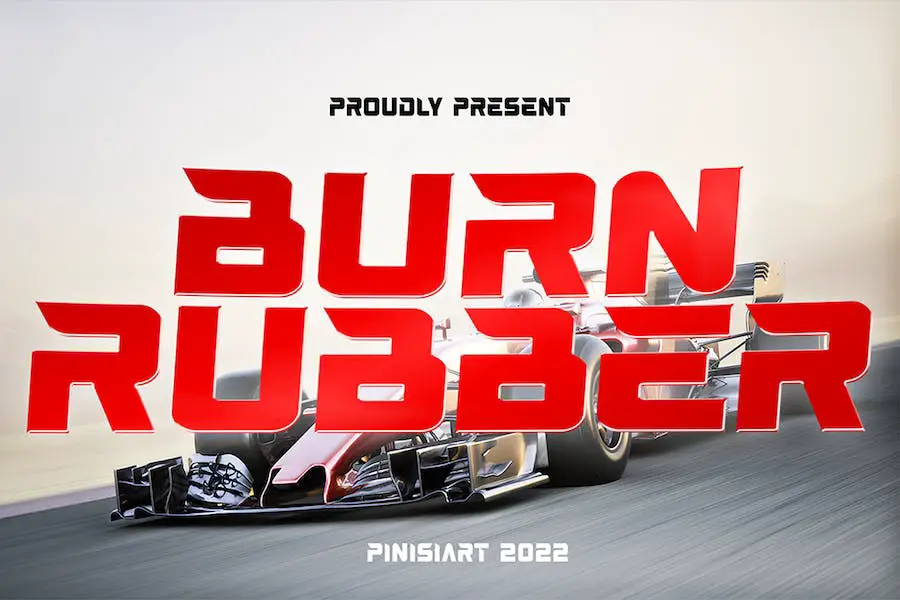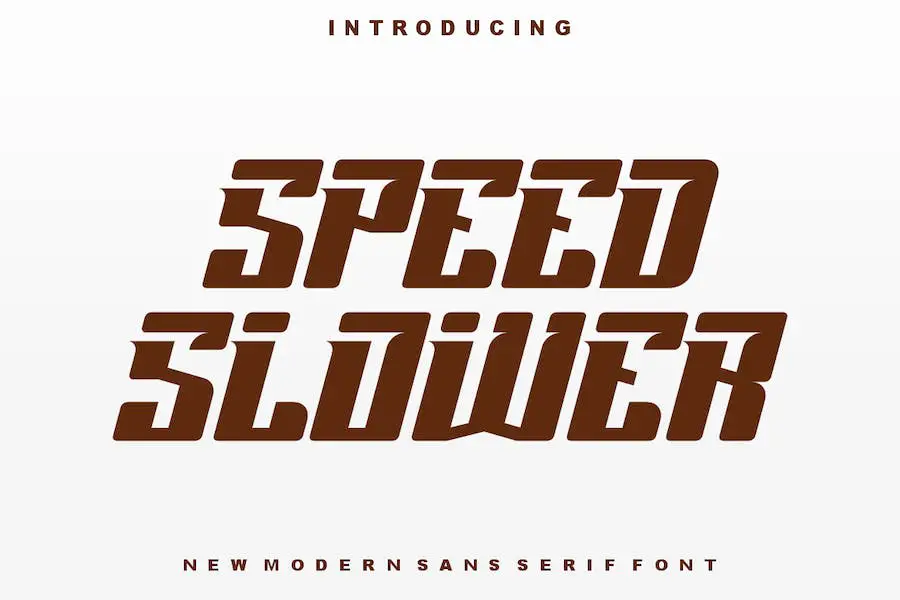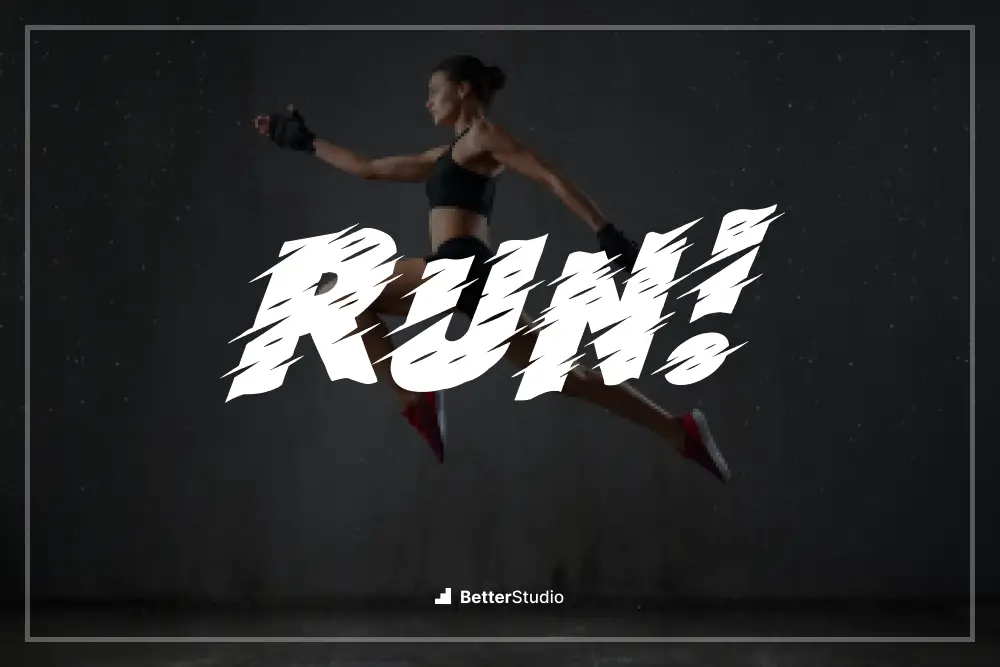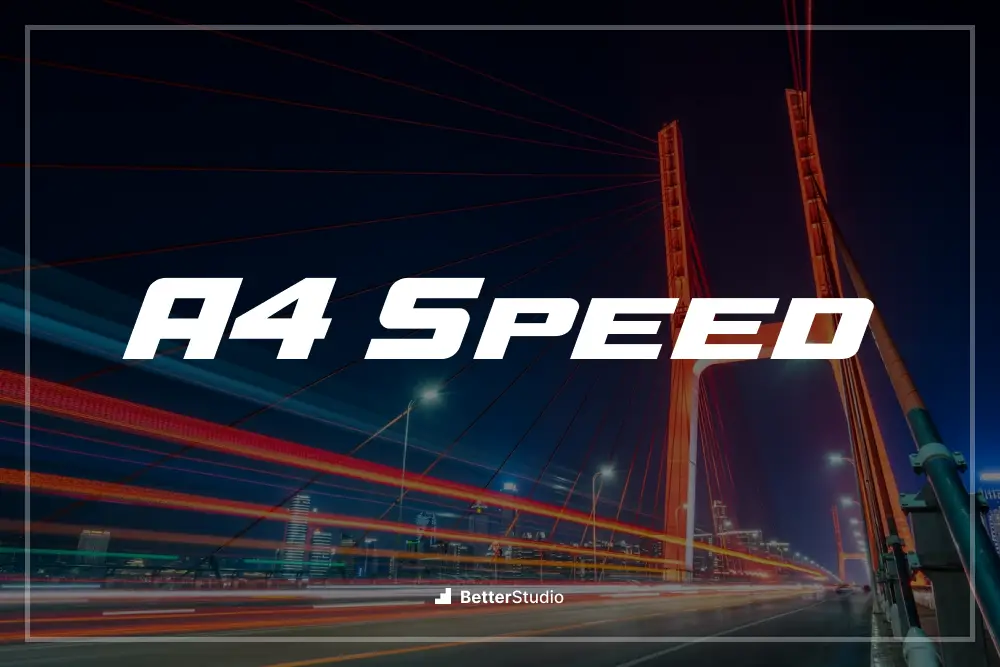
2023 年のベスト Speed フォント 20 (無料およびプレミアム)
公開: 2023-07-31グラフィック デザイン プロジェクトに洗練されたプロフェッショナルな外観を与える完璧なフォントを見つけるのに苦労したことがありますか?
もう探す必要はありません。このブログ投稿では、デザインを次のレベルに引き上げる、無料とプレミアムの両方の 2023 年の最高速度フォント 20 個について説明します。 しかし、なぜスピード フォントに注目するのか疑問に思われるかもしれません。
答えは簡単です。スピード フォントは、可読性と可読性を高めるために特別にデザインされており、視聴者がデザイン内に表示される情報をすぐに吸収できるようになります。
最近の研究によると、インターネット ユーザーの平均注意力持続時間はここ数年で大幅に減少しており、ユーザーの注意を素早く集めることが重要になっています。
実際、調査によると、聴衆に永続的な印象を与えるのに必要な時間はわずか約 8 秒です。
ここでスピードフォントが役に立ちます。 これらのフォントは、すっきりした線、コンパクトな形状、最適化された間隔により、メッセージを迅速かつ簡単に配信します。
この記事では、デザイン プロジェクトを確実に向上させる、厳選された 20 倍速のフォントを紹介します。
ポスター、Web サイト、ロゴ、その他のビジュアル素材のいずれを扱う場合でも、これらのフォントは、視覚的に魅力的で理解しやすいコンテンツを作成するのに役立ちます。
それでは、早速、スピード フォントの世界に飛び込み、次のプロジェクトに最適なタイポグラフィを見つけてみましょう。
最高のプレミアムスピードフォント
高速
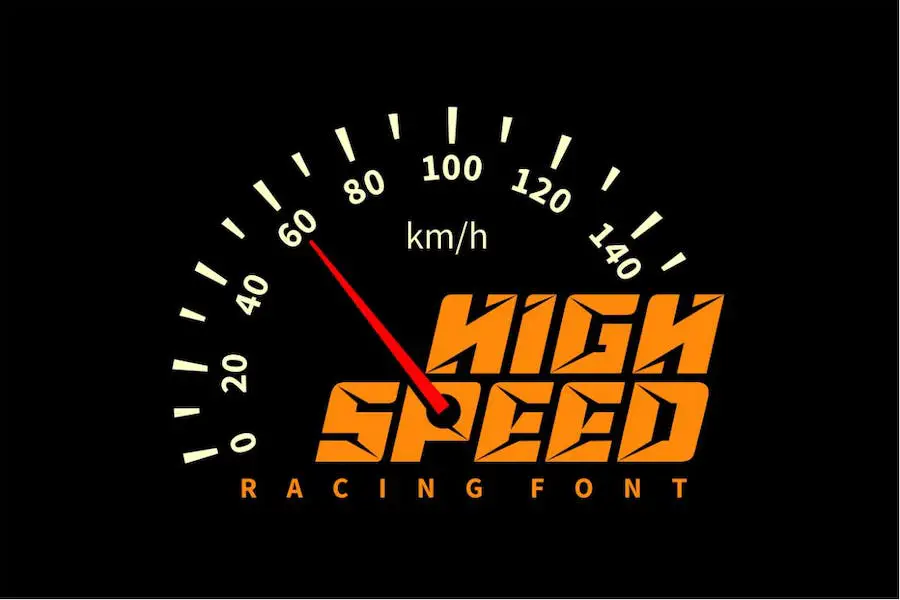
HIGH SPEED は、デザインプロジェクトを大幅に強化するフォントです。 このフォントは、プロジェクトのデザインを改善したいと考えているグラフィック デザイナーに最適です。 HIGH SPEED を使用すると、デザインに新鮮でモダンな外観を与えることができます。
スピードに関して言えば、HIGH SPEED はその名に恥じません。 このフォントは高速読み込み用に最適化されており、デザインがさまざまなプラットフォームで効率的に表示されるようになります。
分数速度
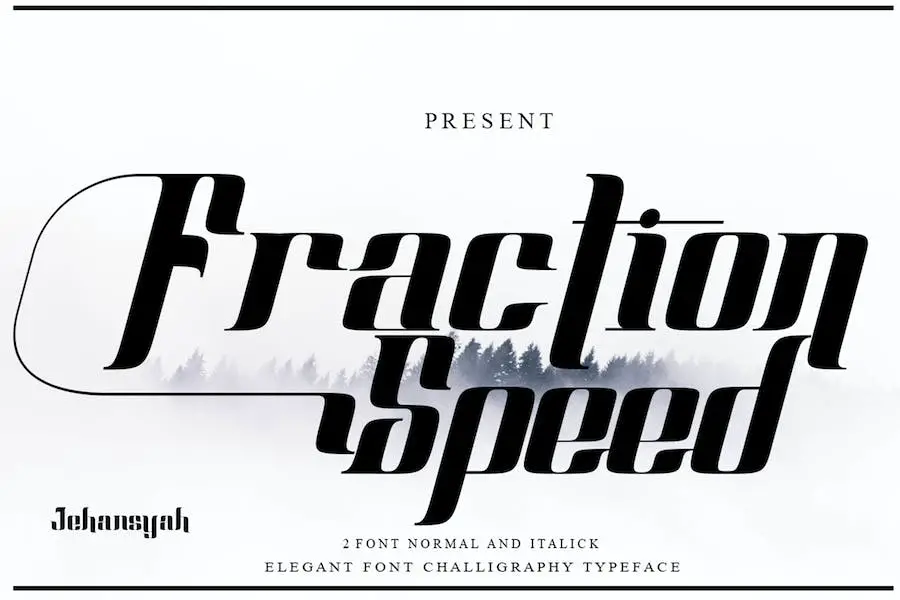
Fraction Speed は、そのプロフェッショナルな外観に驚かされる、驚くほどエレガントなフォントです。 すべてのプロジェクト、特に目を引くタイトルを作成したい場合に最適です。 このフォントは TrueType (ttf) 形式と OpenType (otf) 形式の両方で提供されており、標準スタイルと斜体スタイルの両方で使用できます。
また、必要な句読点、数字、小文字、大文字もすべて含まれており、西ヨーロッパ文字と代替オプションを備えたラテン文字もサポートされています。
Google、Adobe、Word、Canva 用にデザインしている場合でも、タトゥー デザインをデザインしている場合でも、Fraction Speed はデザインを次のレベルに引き上げるのに必要な超高速フォントです。
クイックスターター
QUICKSTARTER は、スピード、レーシング、轟音を立てるマシンのパワーを体現するフォントです。 プロジェクトに高 RPM と興奮の感覚を注入したいグラフィック デザイナーに最適です。
大文字には力強く鋭い角があり、小文字には滑らかで流線型の線画バージョンが付いています。
このフォントは、デザインのレーシングスピリットを真に強調します。 オンライン ゲーム、ポスター、映画タイトル、ファストフード メニュー、雑誌、YouTube のカバー、サムネイル、ソーシャル メディア ページのカバーなど、どのような作業を行っている場合でも、QUICKSTARTER は最適な選択肢です。
スピード持久力
Speed Endurance は、デザイン プロジェクトにモダンなタッチを加えるのに最適な、大胆でエネルギッシュなアスレチック フォント ファミリです。 シャープなラインと検証された傾斜角度により、このフォントはあなたの作品にアスレチックでスポーツにインスピレーションを得た外観を与えます。
スポーツ ゲームのカバー、自動車のデザイン、広告デカール、またはエネルギーを必要とするその他のプロジェクトに取り組んでいる場合でも、Speed Endurance は理想的な選択肢です。 多用途なスタイルにより、幅広い用途に適しています。
Web サイトで作業するグラフィック デザイナー、ラベルを作成するマーケティング担当者、完璧なフォントを探しているタトゥー アーティストのいずれであっても、Speed Endurance は必要な高速でダイナミックな外観を提供します。 この印象的なフォント ファミリーを使用して、デザインを次のレベルに引き上げる準備をしましょう。
ストゥージズ レース
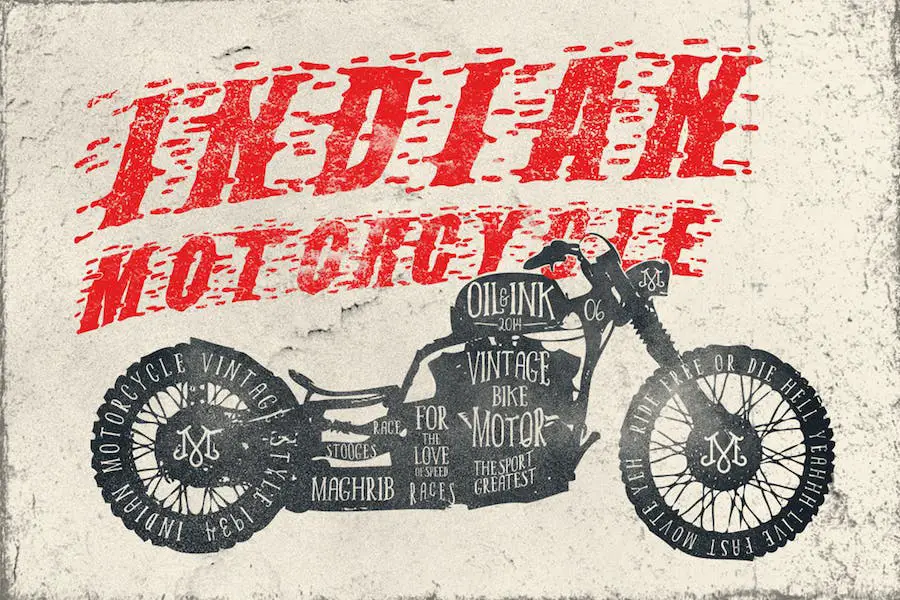
Stooges Races は、デザインに手描きのスタイルをもたらすユニークなフォントです。 1900 年代のオートバイのポスターにインスピレーションを得たこの書体は、あらゆるプロジェクトにヴィンテージでレトロな雰囲気を加えます。
車、自動車のテーマ、デトロイト、1940 年代、50 年代、60 年代のクラシックなマシンを中心としたロゴ、ゲーム、グラフィックに最適です。
このフォントにはベクター シルエットを含むエクストラ パックが付属しており、フォントを最大限に活用するために役立つ Adobe Illustrator のビデオ チュートリアルも用意されています。 Stooges Races を使用すると、デザインに昔ながらの魅力を加えることができます。
ピストンレース
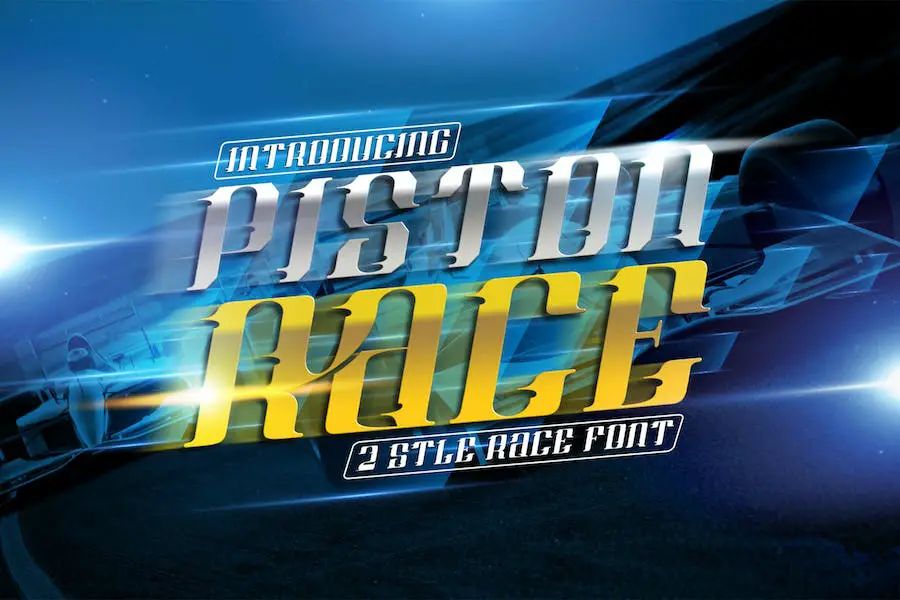
Piston Race は、スポーティなレーシング ディスプレイ フォントからインスピレーションを得たフォントです。 スピード感あふれる精悍で力強い表情を持ち、スポーツレーシングをテーマにしたデザインに最適です。
ロゴ デザイン、車のステッカー、レース イベントのタイトルなど、このフォントはプロジェクトにスピードと興奮を加えるのに最適です。
レースのスピード
Speed of Race は、デザイン プロジェクトにスポーティなレーシング表示スタイルをもたらす素晴らしいフォントです。 大胆さと力強さを醸し出し、スピード感があり、あなたが考えているスポーツやレースをテーマにしたデザインを完璧に引き立てます。
ロゴ デザイン、車のステッカー、レース イベントのタイトルを作成する場合でも、このフォントは頼りになる選択肢です。 そして一番いいところは? デザイン ソフトウェアを使用している場合でも、デザイン以外のプログラムを使用している場合でも、非常に使いやすいです。
スピードゴールデン
Speed of Race は、スポーティなレーシング ディスプレイ フォントからインスピレーションを得たフォントです。 スピード感のある太くて力強いフォントなので、スポーツレーシングをテーマにしたデザインに最適です。
ロゴの作成、車のステッカーのデザイン、レース イベントのタイトルのデザインなど、このフォントはきっと興奮を加えてくれます。 さらに、デザインにさらにスピードとクールさを加えるイタリック版も付属しています。
Speed of Race の優れた点の 1 つは、その多用途性です。 デザイン プログラムと非デザイン プログラムの両方で使用できるため、グラフィック デザイナーとデザイン経験のない人の両方が利用できるようになります。
ハンタースピード
Hunter Speed は、綿密なデジタル化プロセスを経た自然な手作りフォントです。 衣料品、広告、音楽アルバム、ロゴ プロジェクトに取り組むグラフィック デザイナーにとって理想的な選択肢です。
このフォントは、手作りのデザインの美しさとデジタル使用の利便性を簡単に組み合わせています。
スピーダー
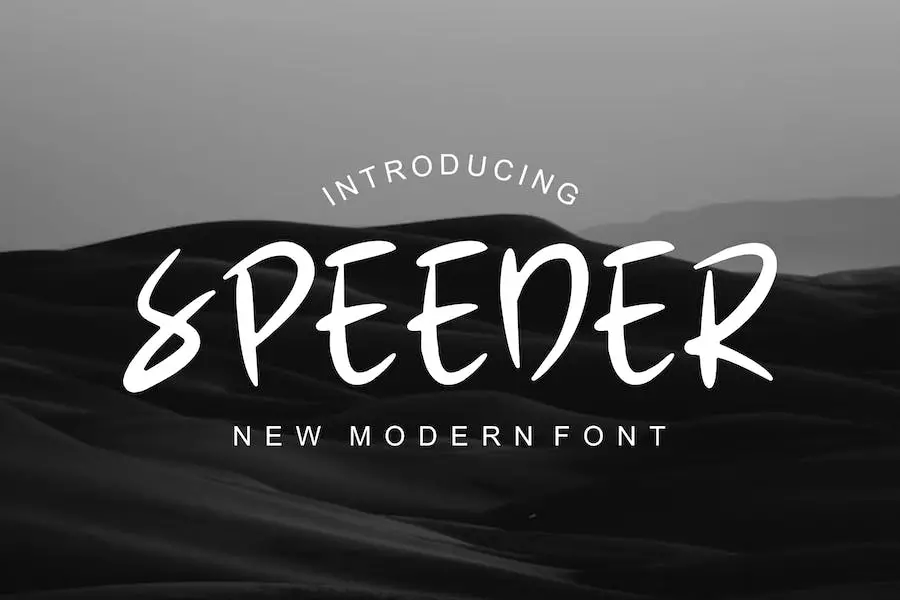
Speeder は、美しさ、品格、優雅さ、そして現代性を醸し出すモダンな手書きフォントです。
署名、文具、ロゴ、結婚式、タイポグラフィーの引用、雑誌や本の表紙、Web サイトのヘッダー、衣類、ブランディング、パッケージ デザインなど、さまざまなプロジェクトに最適です。
この多用途なフォントは男性性と女性性の両方を簡単に表現できるため、ファッション関連のブランディングやエディトリアル デザインに理想的な選択肢となります。 Speeder を使用すると、創造的な取り組みに洗練さと現代的なセンスを加えることができます。
ノクリオス
Nokrios は、レースの世界からインスピレーションを得たフォントで、そのスピードとパワーを表現することを目指しています。 大胆なステートメントを作成し、プロジェクトで目立つこと間違いなしです。
2 つのフォント オプションと 2 つの斜体オプションを備えたこのフォントは、大きく太字のタイトルと小さなアドオン タイプの両方に多用途性を提供します。 小さいサイズでも読みやすさとインパクトを維持できるように設計されています。
Nokrios のすべての機能を十分に体験するには、Adobe アプリや Corel Draw など、OpenType 機能とグリフ パネルをサポートするプログラムを使用することをお勧めします。 これにより、利用可能なグリフのすべてのバリエーションにアクセスして表示できるようになります。
スピードアップ
Speed Up は、ミニマルなスタイルでプロフェッショナルな外観をもたらすシンプルなフォントです。 汎用性が高く、雑誌のタイトル、見出し、オフィスワーク、本の表紙など、さまざまな形で使用できます。
このフォントは、面白いプロジェクトにもフォーマルなプロジェクトにも最適で、あらゆるデザインに適しています。 大文字と小文字の両方のスタイルを備えており、ロゴからバナーまで、あらゆるアートワークに簡単に統合できます。
スピード狂
Speed Demon は、デザインにスピード感と興奮を瞬時にもたらすフォントです。 その洗練されたモダンなデザインは、ペースの速いカーレースの世界の本質を捉えています。
Speed Demon の大きな特徴の 1 つは、その多用途性です。 きれいな線と太いストロークにより、小さなサイズでも読みやすくなっています。
結論
結論として、スピード フォントの世界と、スピード フォントがグラフィック プロジェクトのデザインをどのように大幅に改善できるかを調査してきました。
適切なフォントを選択することの重要性、それが読みやすさとユーザー エクスペリエンスに与える影響、および利用可能な最高速度のフォント オプションについて説明しました。